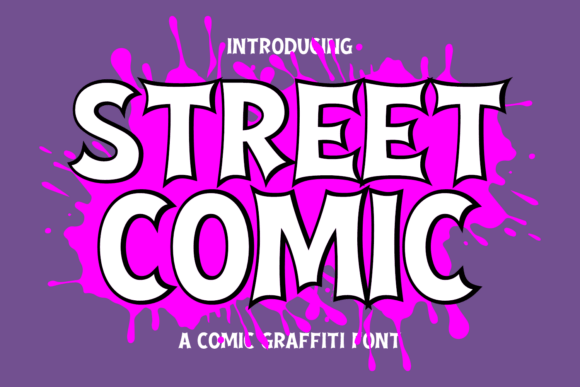
Street Comic
Jika Anda mencari aset berkualitas tinggi seperti Street Comic, paket premium ini adalah pilihan fantastis untuk proyek kreatif Anda.
Baik Anda membuat produk POD (Print on Demand), undangan pernikahan, atau grafis media sosial, Street Comic adalah pilihan yang sangat ideal.